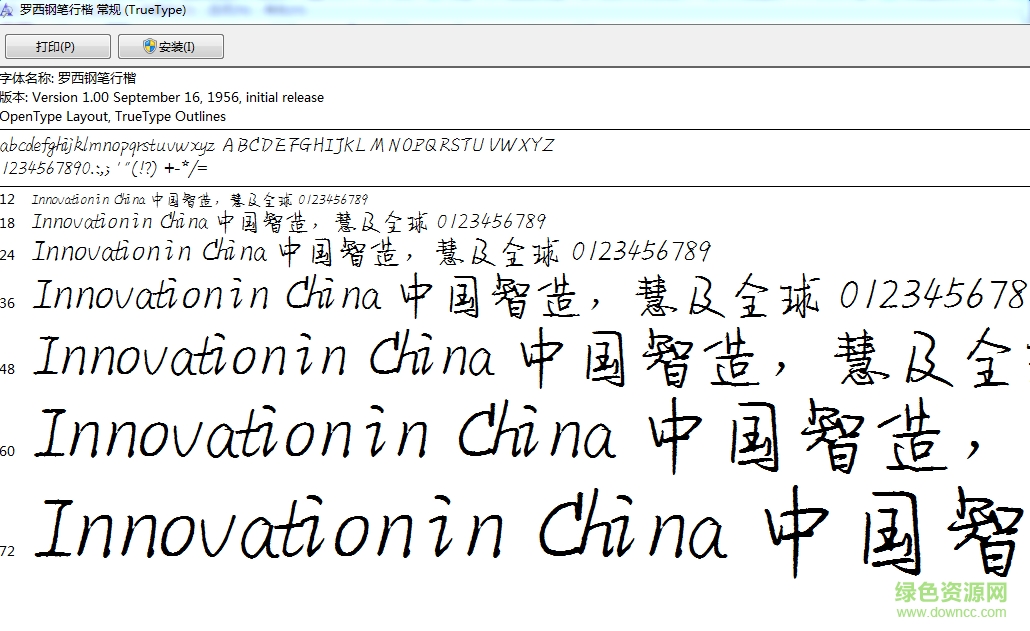
羅西鋼筆行楷加粗是在常規(guī)體的羅西鋼筆行楷上轉(zhuǎn)變后的字體,讓字跡顯得更加深刻大方,舒暢流利的模型深得創(chuàng)意設(shè)計(jì)人士的喜愛(ài),綠色資源網(wǎng)免費(fèi)推薦!
羅西鋼筆行楷是一款不可多得的鋼筆手寫(xiě)字體,結(jié)合行楷的特色,字跡鏗鏘不拖沓,給你沉重端莊之感,廣泛適用于廣告設(shè)計(jì)、平面設(shè)計(jì)、藝術(shù)創(chuàng)作、印刷包裝、個(gè)性簽名等領(lǐng)域。